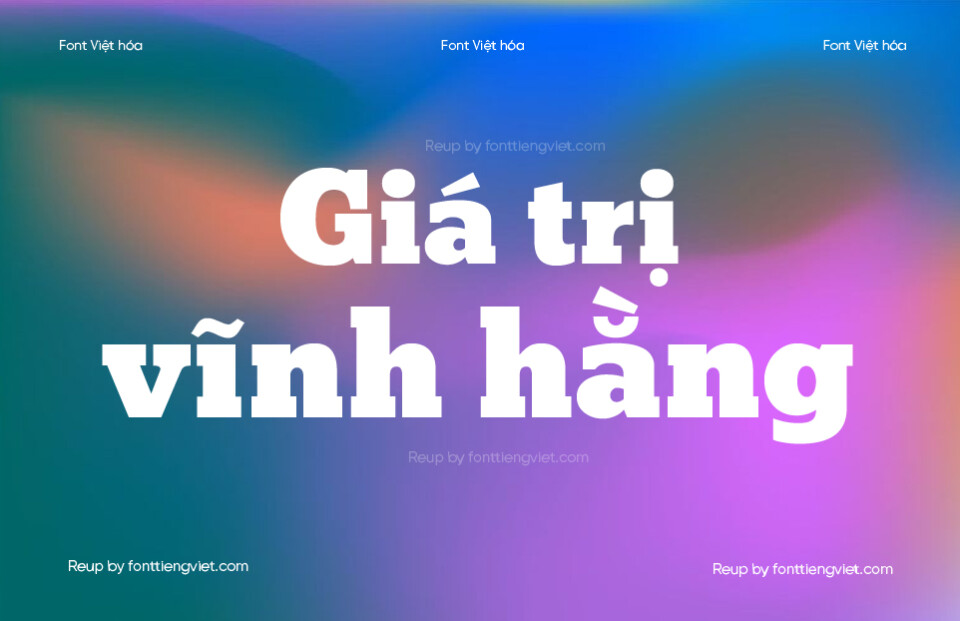
Trong thế giới thiết kế đồ họa, việc lựa chọn một Font Chữ ấn tượng và dễ đọc là yếu tố then chốt. Đặc biệt, đối với các bạn học sinh, sinh viên hay những người làm công tác giáo dục, việc sử dụng font chữ có tính thẩm mỹ cao lại càng quan trọng để tạo ra các tài liệu học tập, báo cáo hay ấn phẩm truyền thông thu hút. Và đó là lý do vì sao Font Việt hóa UTM Bevan lại trở thành cái tên được tìm kiếm nhiều nhất. Bài viết này sẽ đi sâu vào những ưu điểm nổi trội của UTM Bevan phiên bản Việt hóa và hướng dẫn bạn cách tải về sử dụng một cách nhanh chóng nhất, giúp bạn tối ưu hóa các ấn phẩm từ bài thuyết trình cho đến tài liệu ôn thi tốt nghiệp.
Tại sao Font Việt hóa UTM Bevan lại được yêu thích trong môi trường giáo dục?
Font Việt hóa UTM Bevan không chỉ là một phông chữ đẹp mắt mà còn sở hữu những đặc tính Typography mạnh mẽ, rất phù hợp cho các dự án liên quan đến trường học, từ cấp trung học phổ thông (high school students) cho đến đại học. UTM Bevan thuộc kiểu chữ slab serif mạnh mẽ, đậm nét, tạo cảm giác chắc chắn và đáng tin cậy. Chính sự mạnh mẽ này giúp nội dung truyền tải trở nên nổi bật, rất lý tưởng cho các tiêu đề, poster thông báo hoặc thiết kế logo đội nhóm.
Phiên bản Việt hóa của UTM Bevan đảm bảo rằng mọi ký tự tiếng Việt, bao gồm các dấu câu và dấu thanh, đều được hiển thị một cách chính xác và mượt mà, loại bỏ hoàn toàn lỗi font thường gặp. Điều này cực kỳ quan trọng đối với các bạn học sinh, sinh viên đang chuẩn bị cho các kỳ thi tốt nghiệp (graduation exams) hay làm luận văn, nơi tính chính xác của văn bản được đặt lên hàng đầu.
Đặc điểm thiết kế của UTM Bevan: Sự kết hợp giữa cổ điển và hiện đại
Thiết kế của Bevan có nguồn gốc từ các kiểu chữ quảng cáo đầu thế kỷ 20, mang hơi hướng cổ điển nhưng vẫn giữ được nét hiện đại nhờ các đường nét tinh tế, không quá cầu kỳ. Đây là một lợi thế lớn khi áp dụng vào các ấn phẩm truyền thông của trường học, giúp truyền tải thông điệp một cách rõ ràng nhưng vẫn giữ được tính nghệ thuật.
- Độ đậm cao: Phù hợp cho tiêu đề chính, đảm bảo thu hút ánh nhìn ngay lập tức.
- Khả năng đọc tốt: Mặc dù là font đậm, nhưng các nét chữ được thiết kế rõ ràng, không gây khó khăn cho người đọc, kể cả khi dùng trong khổ lớn.
- Tính đa dụng: Có thể sử dụng trong nhiều ngữ cảnh khác nhau, từ báo tường, brochure giới thiệu trường, cho đến bài thuyết trình của sinh viên.
Ứng dụng thực tiễn của font chữ này cho học sinh và sinh viên
Đối với học sinh trung học phổ thông và sinh viên, việc làm quen và sử dụng các công cụ thiết kế, trong đó có font chữ, là một kỹ năng cần thiết. Font Việt hóa UTM Bevan là công cụ tuyệt vời để nâng cao chất lượng các sản phẩm học thuật và sáng tạo cá nhân.
Các ứng dụng phổ biến bao gồm:
- Thiết kế bìa báo cáo và luận văn: Một bìa báo cáo đẹp mắt với tiêu đề nổi bật bằng UTM Bevan sẽ tạo ấn tượng mạnh với giáo viên ngay từ cái nhìn đầu tiên.
- Tài liệu ôn thi và Slide thuyết trình: Sử dụng font này cho các điểm nhấn quan trọng trong slide giúp học sinh dễ dàng tập trung vào kiến thức cốt lõi.
- Sản phẩm truyền thông cho sự kiện trường: Từ poster tuyển tình nguyện viên cho đến banner chào đón tân sinh viên, UTM Bevan luôn hoàn thành xuất sắc nhiệm vụ thu hút sự chú ý.
Đây là một tài nguyên quý giá, đặc biệt là với các bạn học sinh đang trong giai đoạn nước rút chuẩn bị cho kỳ thi tốt nghiệp THPT, cần thiết kế các tài liệu tóm tắt kiến thức một cách khoa học và đẹp mắt. Việc sử dụng font chữ chuyên nghiệp thể hiện sự nghiêm túc và đầu tư vào chất lượng sản phẩm.